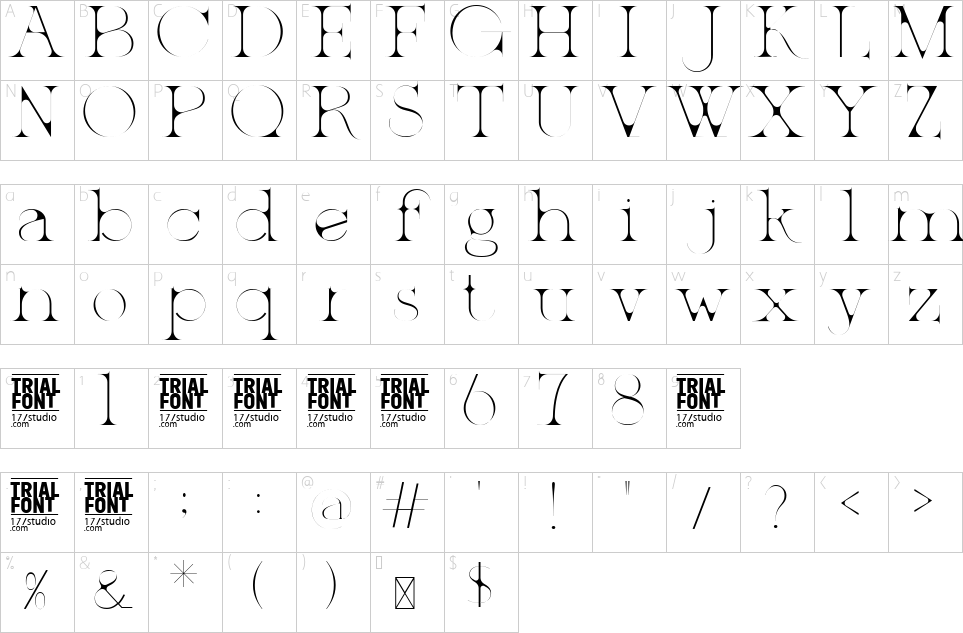
A fonte Patented Ramesh é uma criação inovadora e elegante disponível para download, oferecendo designers e entusiastas do design uma opção de fonte única para seus projetos de design gráfico. Desenvolvida pela 177Studio.com, esta fonte foi projetada para complementar uma variedade de estilos e formatos de layout. Ela é uma escolha ideal para aqueles que buscam uma fonte moderna e versátil, capaz de adaptar-se facilmente a diferentes tamanhos e formatos de texto. A fonte Patented Ramesh já foi baixada 864 vezes, demonstrando seu valor e popularidade entre os designers. Essa fonte gratuita está disponível tanto para sistemas Windows quanto para Mac, tornando-a uma opção conveniente para designers de todos os níveis. Com sua rica variedade de estilos e formas, a Patented Ramesh está em constante evolução, mantendo-se atualizada e adaptada para atender às necessidades das mais variadas criações gráficas.